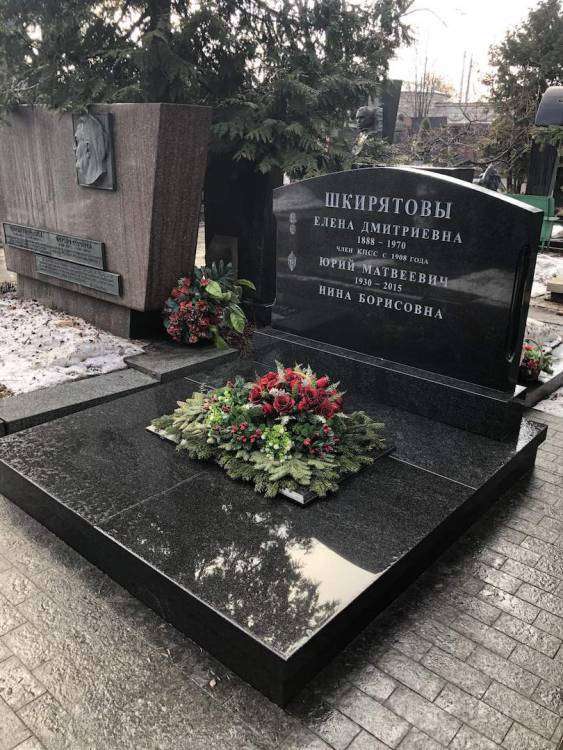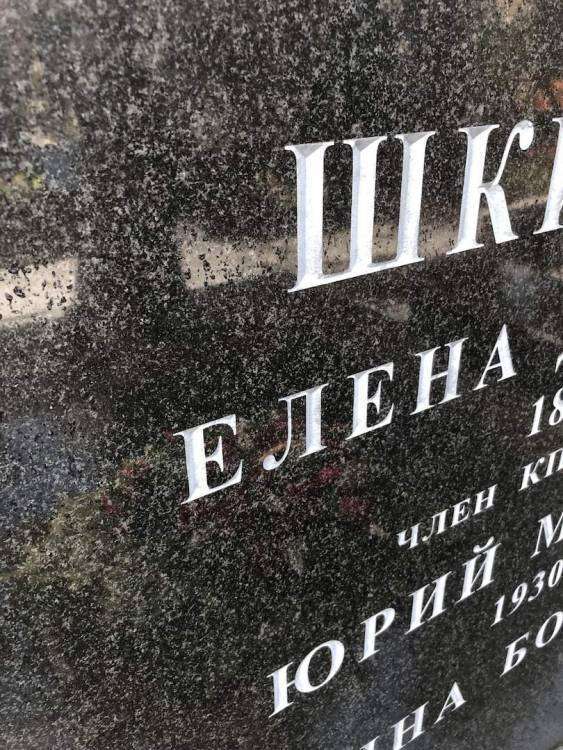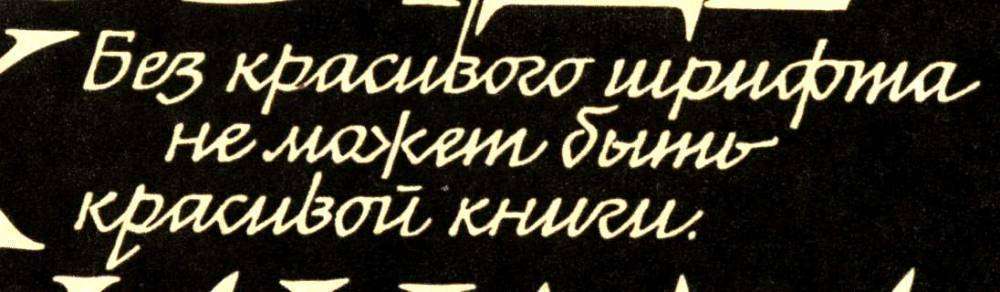
Помогите найти шрифт!
Не, у меня самоотвод в виду невероятной лени наших словорубов, а мой фрезер на уралвагонзаводе ещё не собрали, правильную букву буду делать именно в потоке чуть позже :)
Подскажите название шрифта
Похож на  a_Presentum
Похож да не он, это древний какой-то, походу в цифре не найти
У Госзнака во времена СССР была своя подборка шрифтов. Это один из них.
Я тут поковырялся в сети, тоже цифрового варианта не нашёл..
Подскажите пожалуйста название шрифта
Добрый день! Понравился шрифт. Я так понял это на " ус". Буквы с тенями. Как это достигается... глубина рубки, качественная  зачистка поверхности  вырубленной буквы, размеры буквы. Мне показалось, что буквы покрашены под серебро или серой краской, или палладий?
Это ручная работа.Правда шрифт уже компьютерный-распечатан из заглавных.
Добрый день! А за счет чего тени? Угол рубки, глубина?
А за счет чего тени? Угол рубки, глубина?
Тени именно из-за глубины и угла.
Какая должна быть глубина и угол?
нет  стандартов на угол и/или глубину.
тень будет видна при любой (практически) глубине. Чем ярче солнце, тем виднее тень.
на фото так на вскидку - градусов 100-105 угол.
глубина не постоянна, постоянен угол, соответственно, чем шире элемент - тем глубже.
на фото - не обязательно палладий. возможно - сусальное серебро. в худшем - серебристая (либо серая) краска.
Добрый день! Сусальное серебро темнеет со временем? Палладий светлее смотрится?
тут не подскажу, я только с золотом близко знаком.
Палладием кроем, но мне на столько не нравится после золота-ужас.Да и золото-то разное, в нём много предпочтений у мастеров :)
Но это меня скорее сила привычки, стереотип.
А про "сусальное серебро" даже не слышал :)
нид хелп-как звать этого парня??? ни один буржуйский поисковик не признает в лицо
Буква "С"-  MAGISTRAL, "ТАНДАРТ"-  ARIAL.
р - так-то тоже не родная.
обычная ручная отсебятина. предположу, что ее автор не любит рисовать округлые элементы...
предположу, что ее автор не любит рисовать округлые элементы...
скорее плотер плохо режет - недорезает